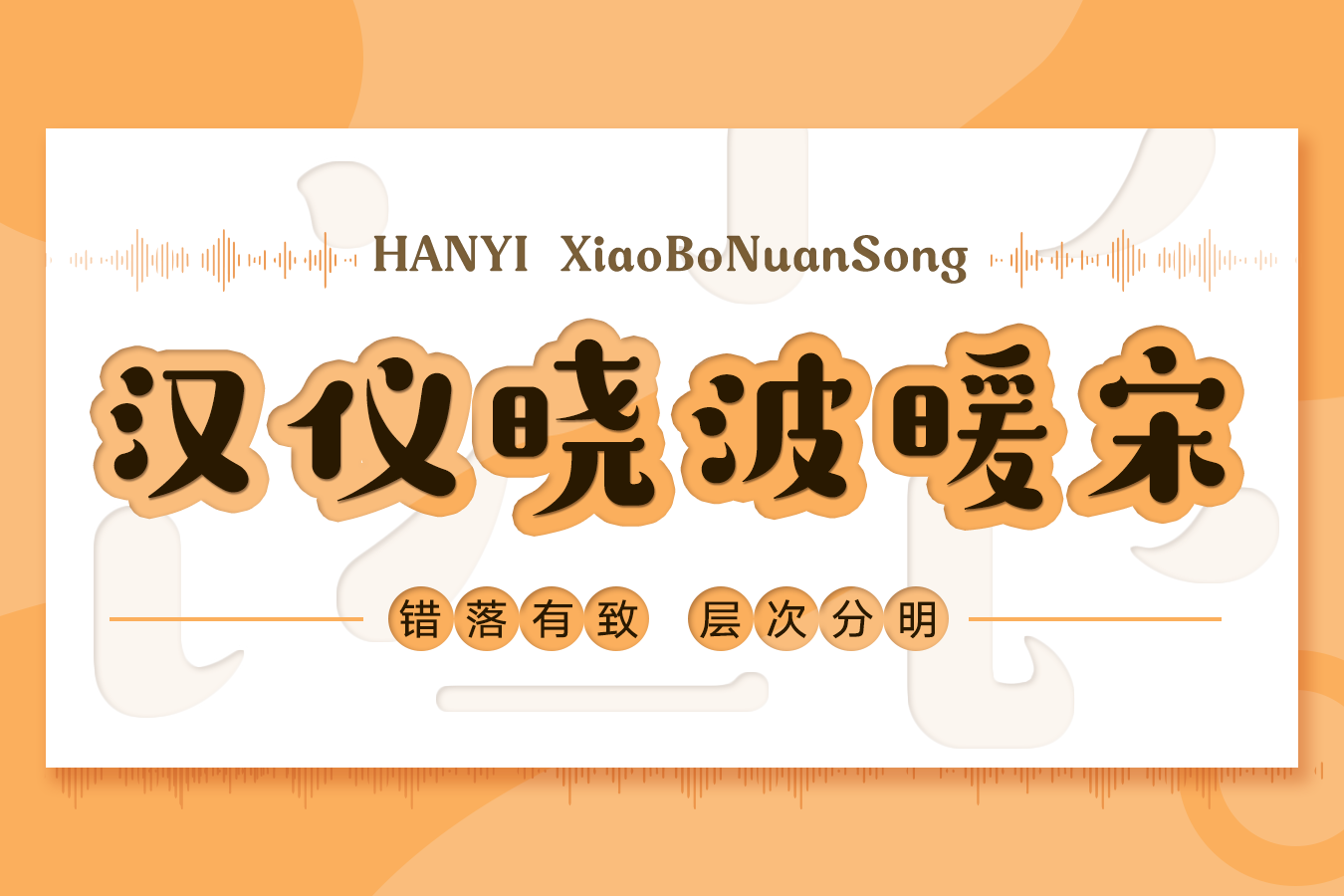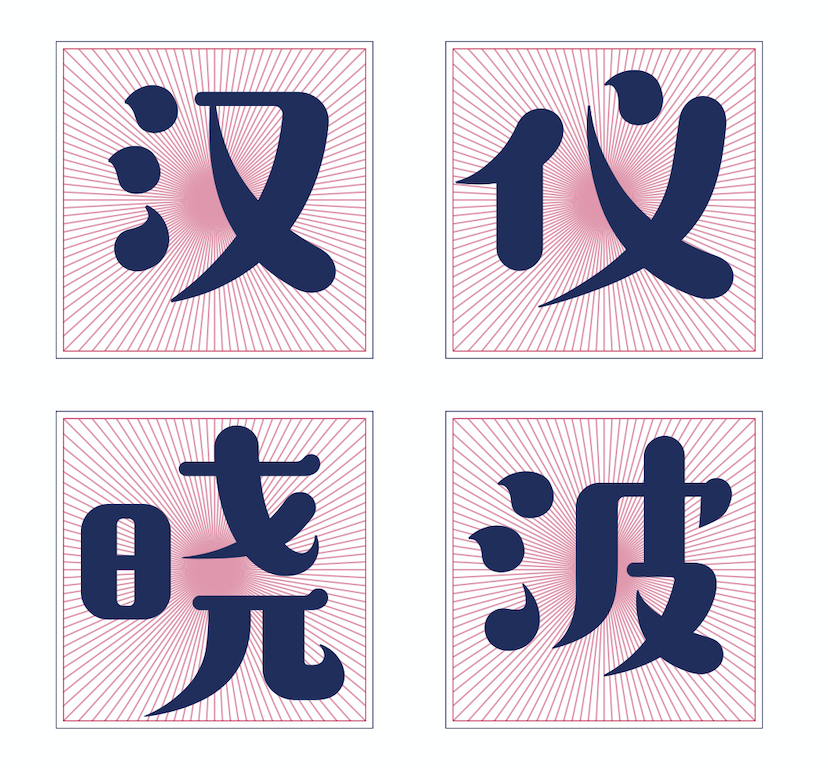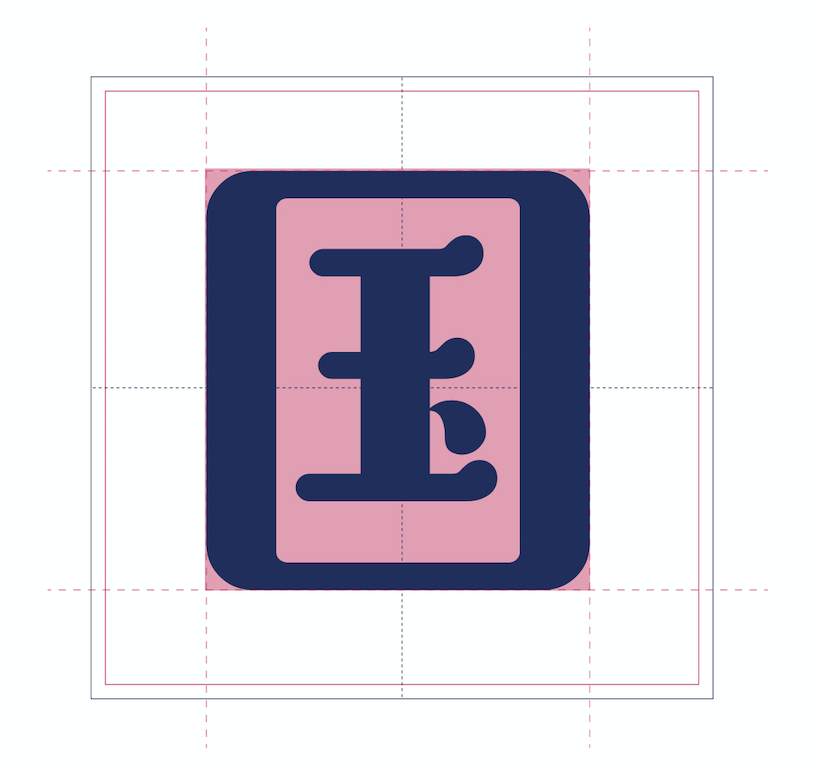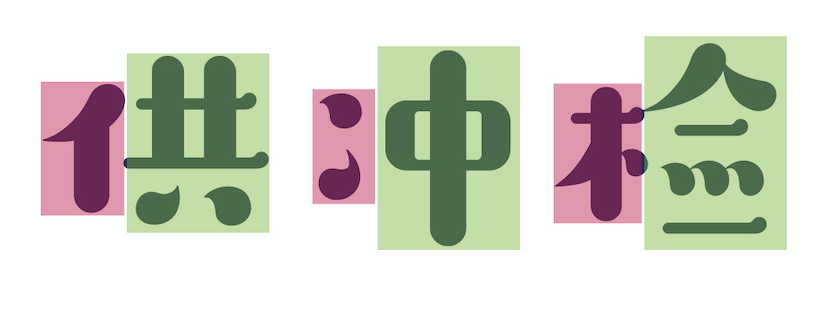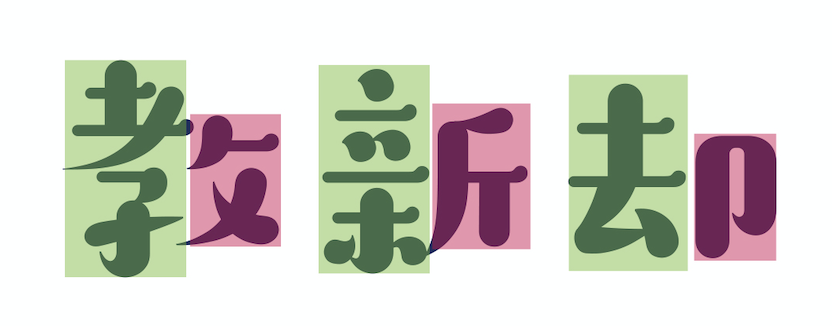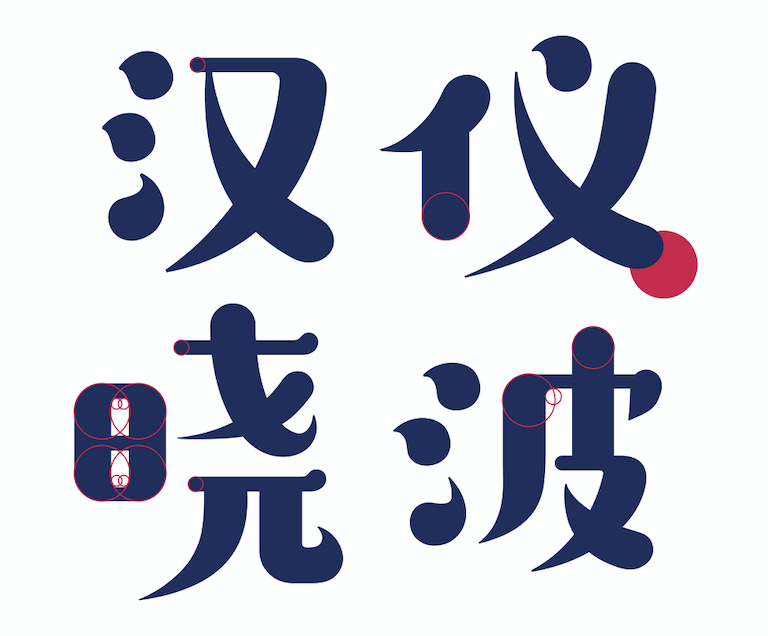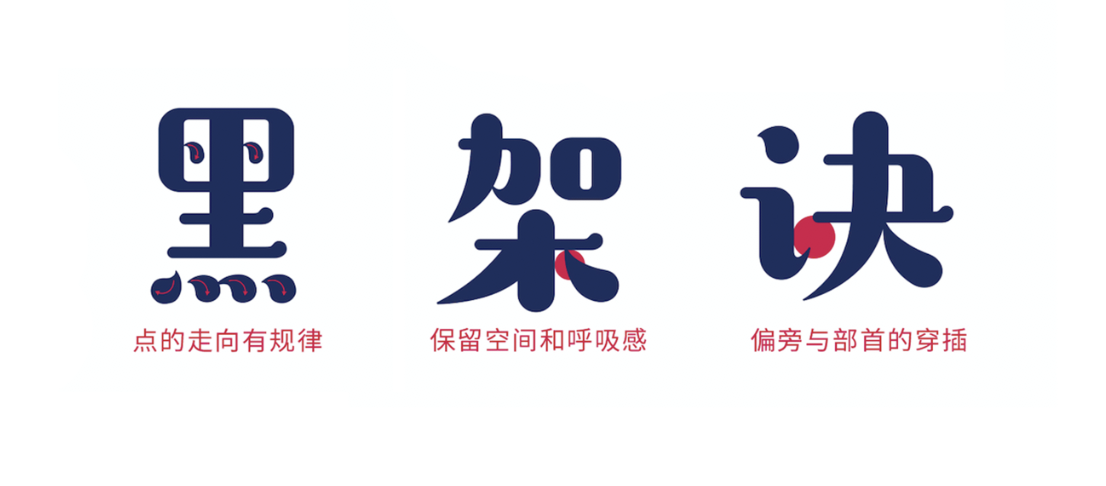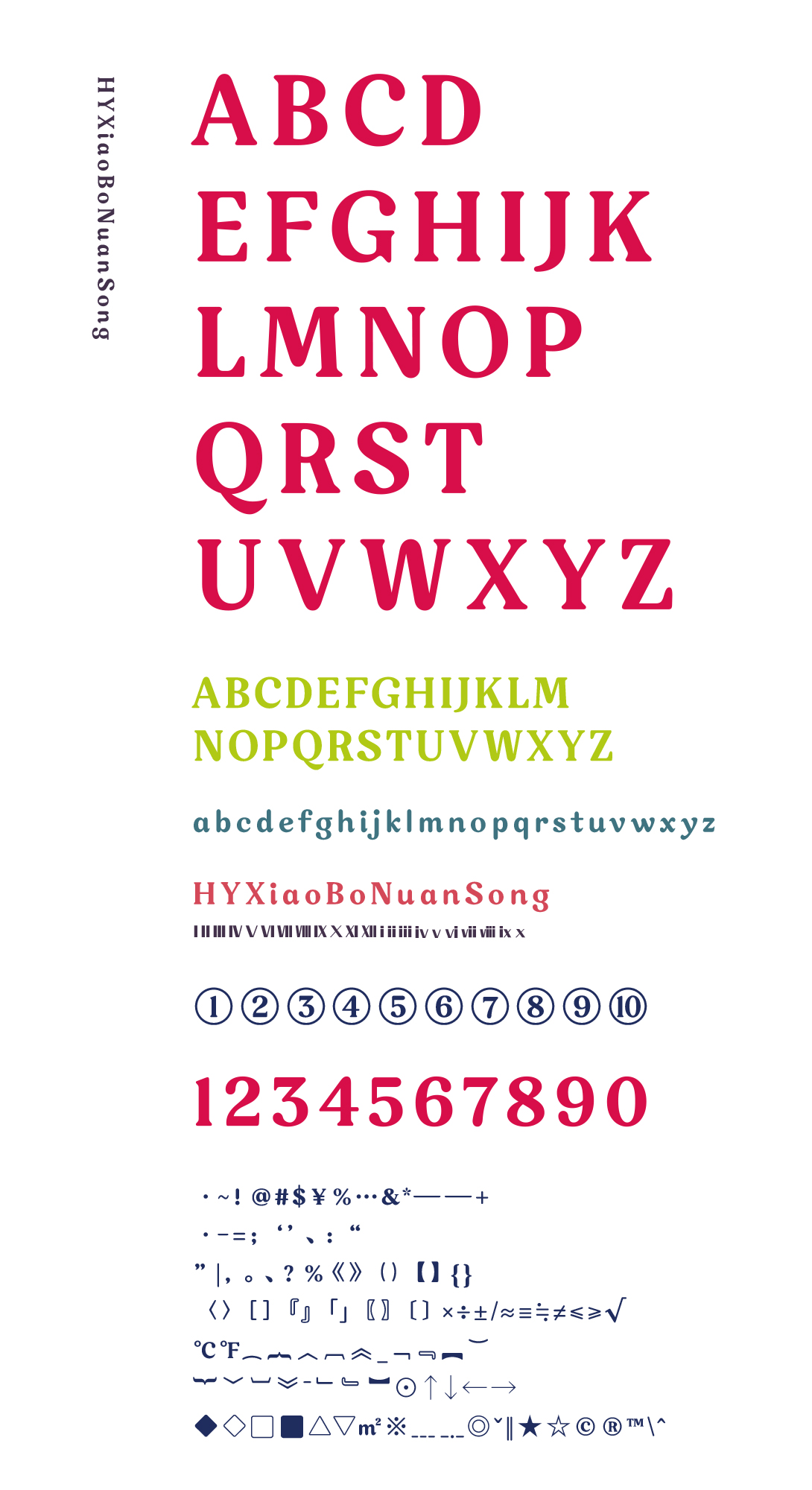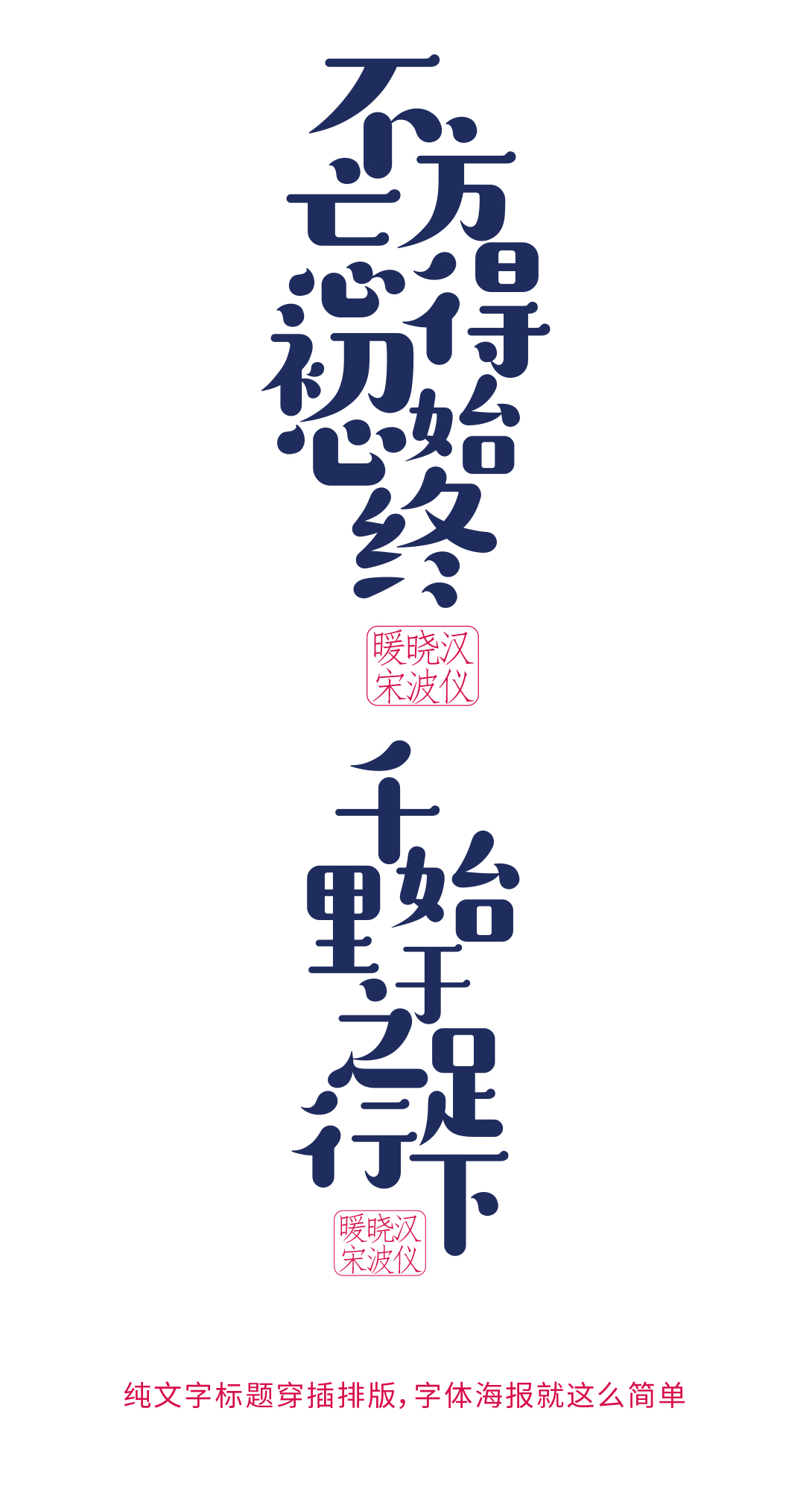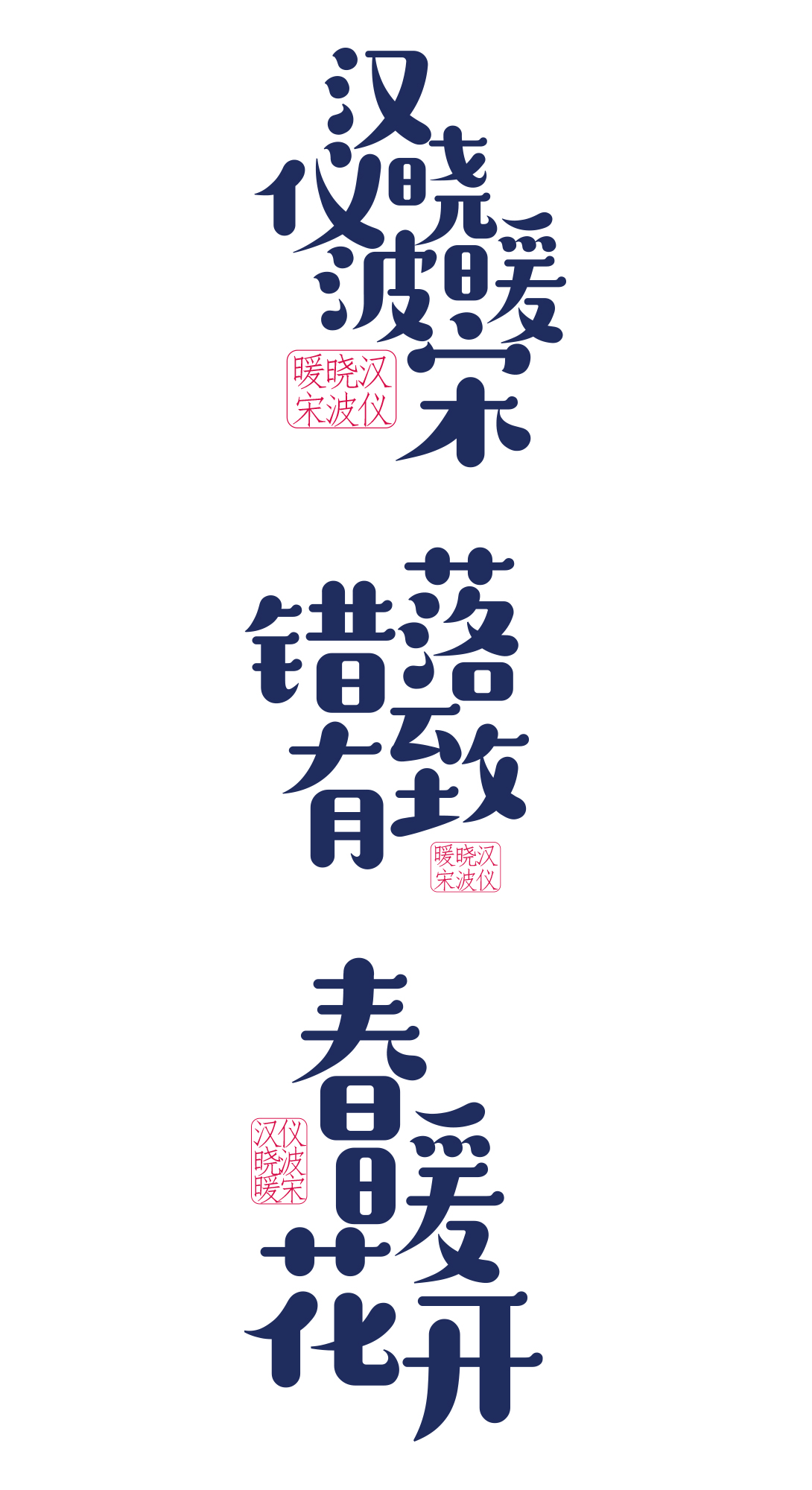
汉仪晓波暖宋字体介绍,一款活泼可爱,富有节奏感的标题字
汉仪晓波暖宋 | 整体特点
汉仪晓波暖宋是一款活泼可爱,富有节奏感的标题字。
汉仪晓波暖宋 | 字形结构
汉仪晓波暖宋的重心居中,富有凝聚力,结构虽然错落但依旧井然有序。
汉仪晓波暖宋的方框字形版率大大缩小。
汉仪晓波暖宋的偏旁与部首版率占比差距大,单字结构变化丰富,经久耐看。
汉仪晓波暖宋 | 笔画特点
汉仪晓波暖宋在保留了宋体字横细竖粗的基础上将笔画的棱角化圆,丰富细腻的曲线使这款字饱含了更多的温情。粗细不一的笔画搭配错落有致的结构让字体变得层次分明,俏皮灵动。
汉仪晓波暖宋的“点”笔画走向规律。部分笔画之间留有空隙,保留了空间和呼吸感。
汉仪晓波暖宋 | 西文符号展示
汉仪晓波暖宋 | 排版效果
汉仪晓波暖宋适合作为大标题使用,推荐字号在20pt以上。
汉仪晓波暖宋 | 案例展示